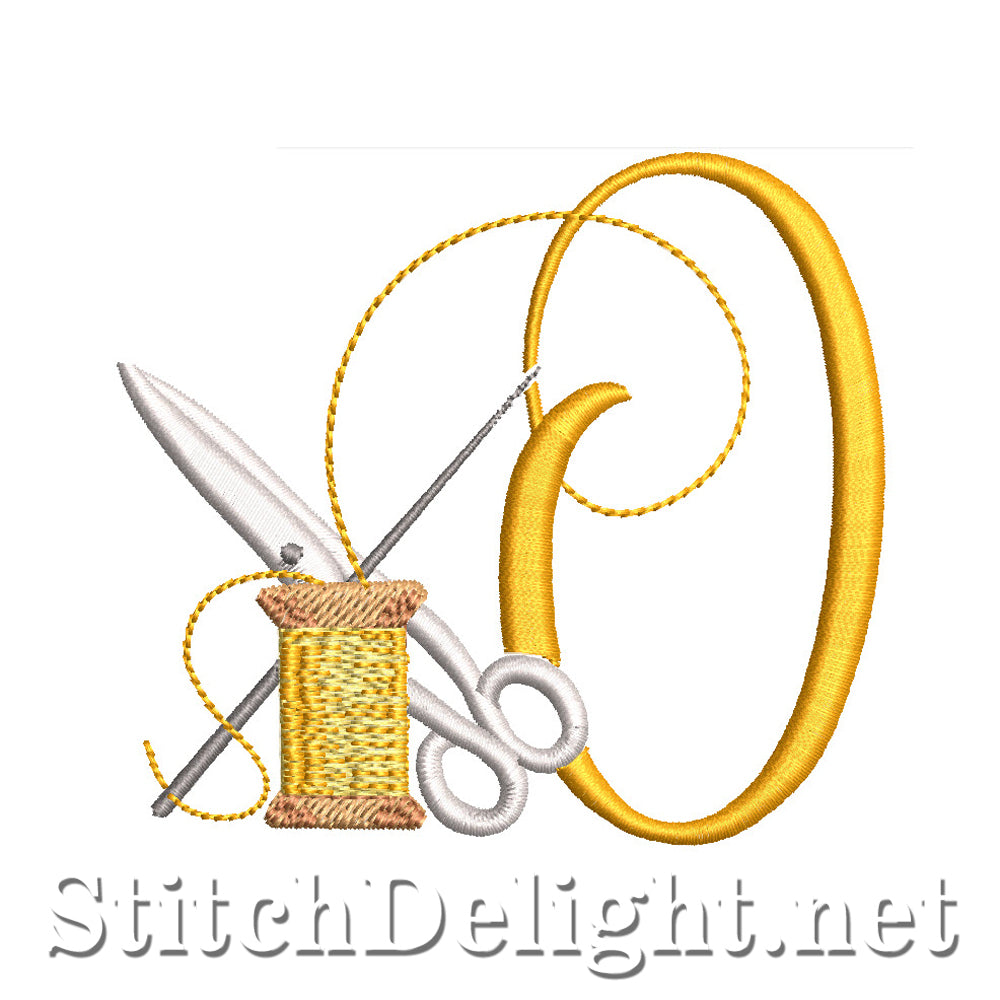
SDS1773 Stitch Delight Police O
Le nom de cette police est Stitch Delight car c'est la même police que nous avons utilisée dans notre logo ! Il a une hauteur moyenne de 3,3" et a SEULEMENT 6 couleurs ! Les deux SDS1764 et SDS5401 feront d'excellentes polices assorties.